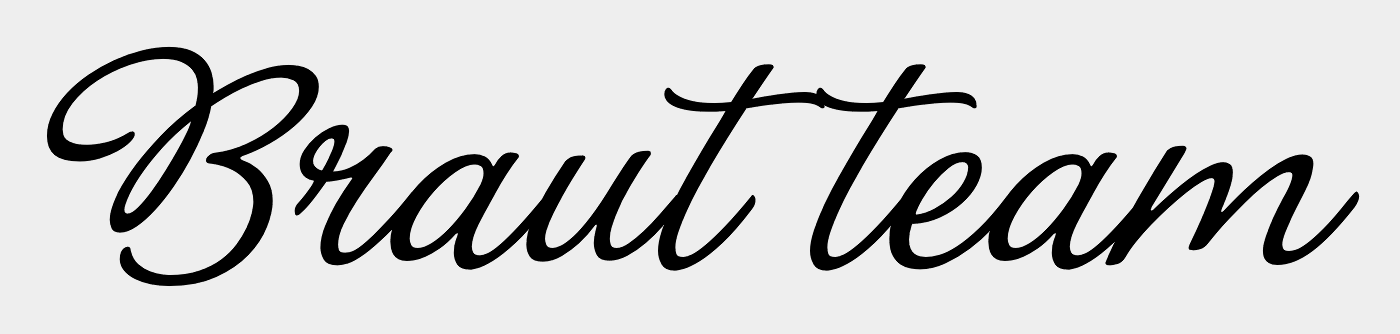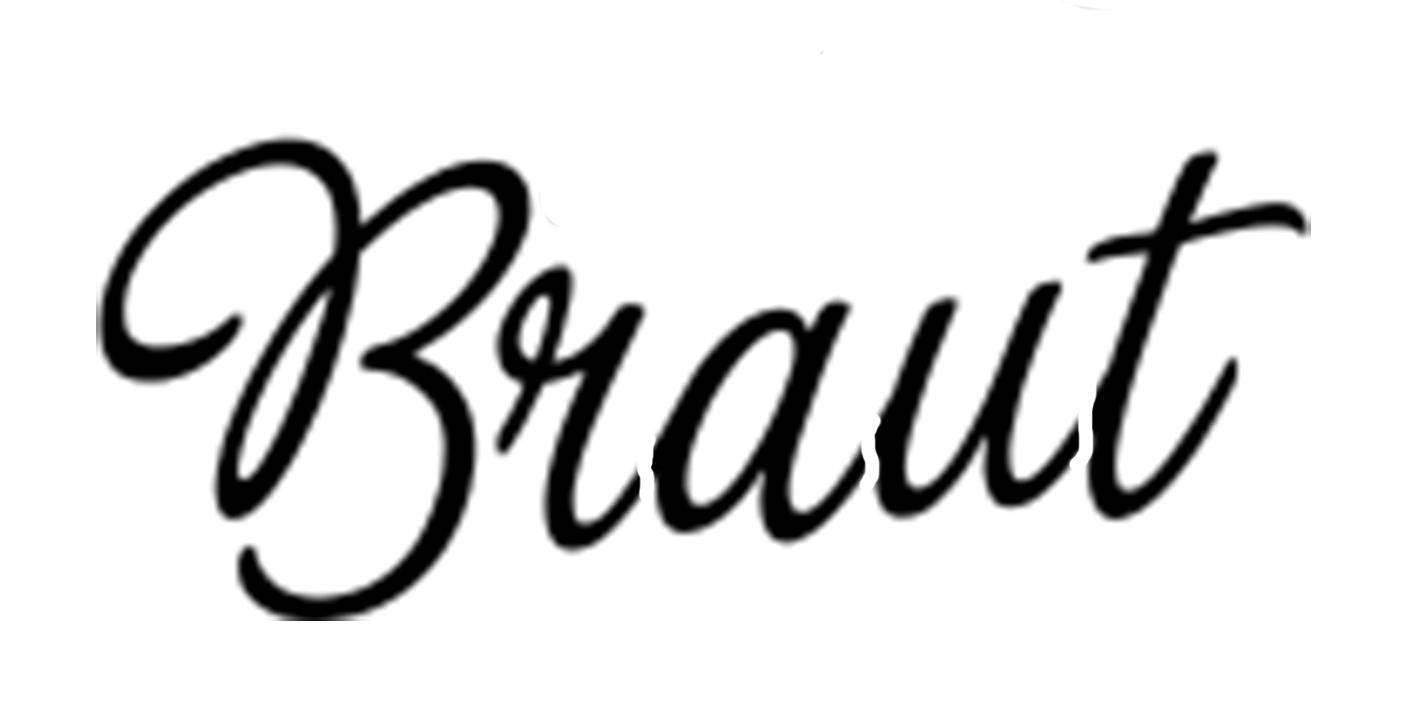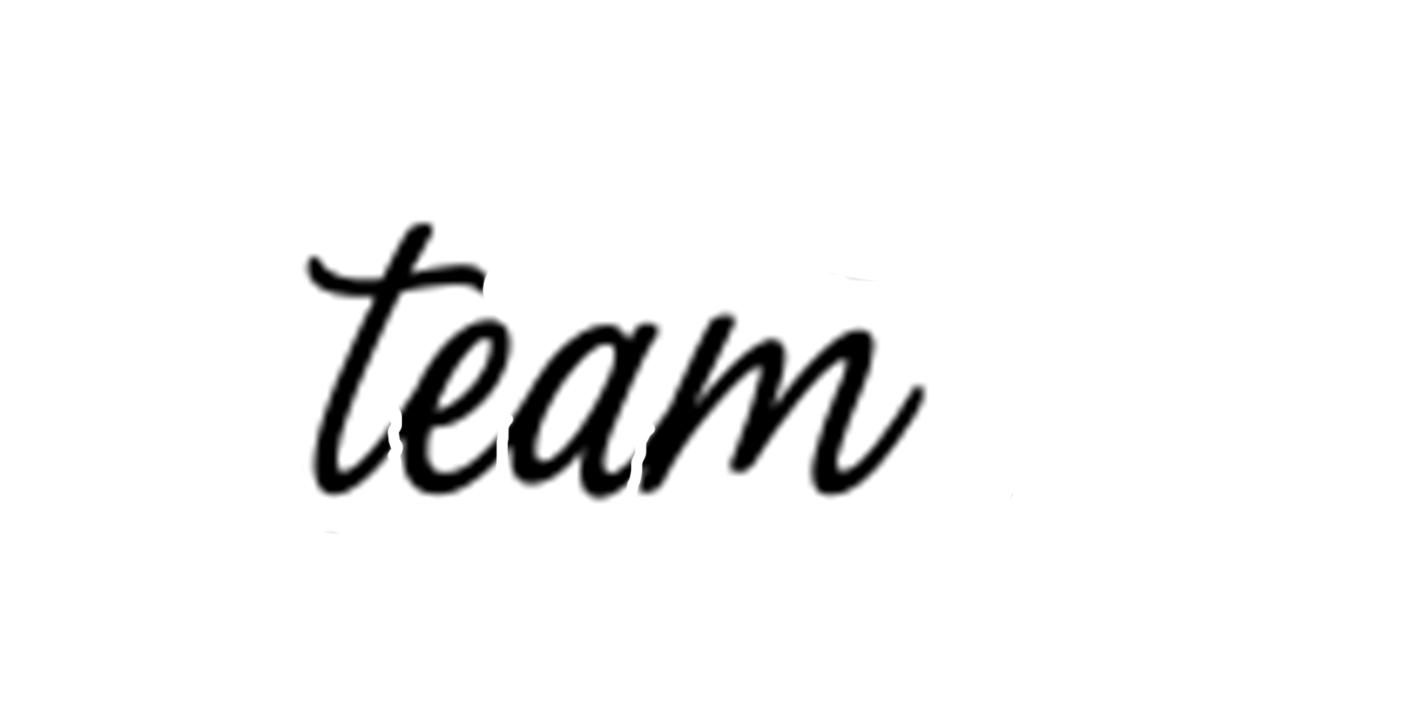
Ich verzweifel an dieser Schriftart...HILFE
kann mir jemand sagen wie diese Schriftart heißt ????
habe jetzt 3 stunden damit verbracht das halbe Internet zu durchsuchen =(
Der Designer nennt sich Ellumination vielleicht hilft das ja beim beantworten meiner Frage !
Die Buchstaben der beiden Worte sind offensichtlich sehr unterschiedlich. Vielleicht handelt es sich nicht um einen Font, sondern um einen gezeichneten Schriftzug. Wo hast Du das gefunden?
Horizontal gequetscht.
Die Schriftart wird von ein und dem selben Künstler benutzt, der T-Shirt-Druckvorlagen macht. hier der LINK
Aus reiner neugier...wie hast du die Schriftart gefunden?
Ich hatte nach dem Schriftzug gegoogelt und herausgefunden, dass er bei freaky-shirts und anderen angeboten wird. Hier gab es dann auch eine weniger verzerrte Version namens "Bräutigam", von dieser einen Screenshot gemacht, in Einzelbuchstaben zerlegt und whatfontis.com bemüht. Voilà, heraus kam die La Portenia.